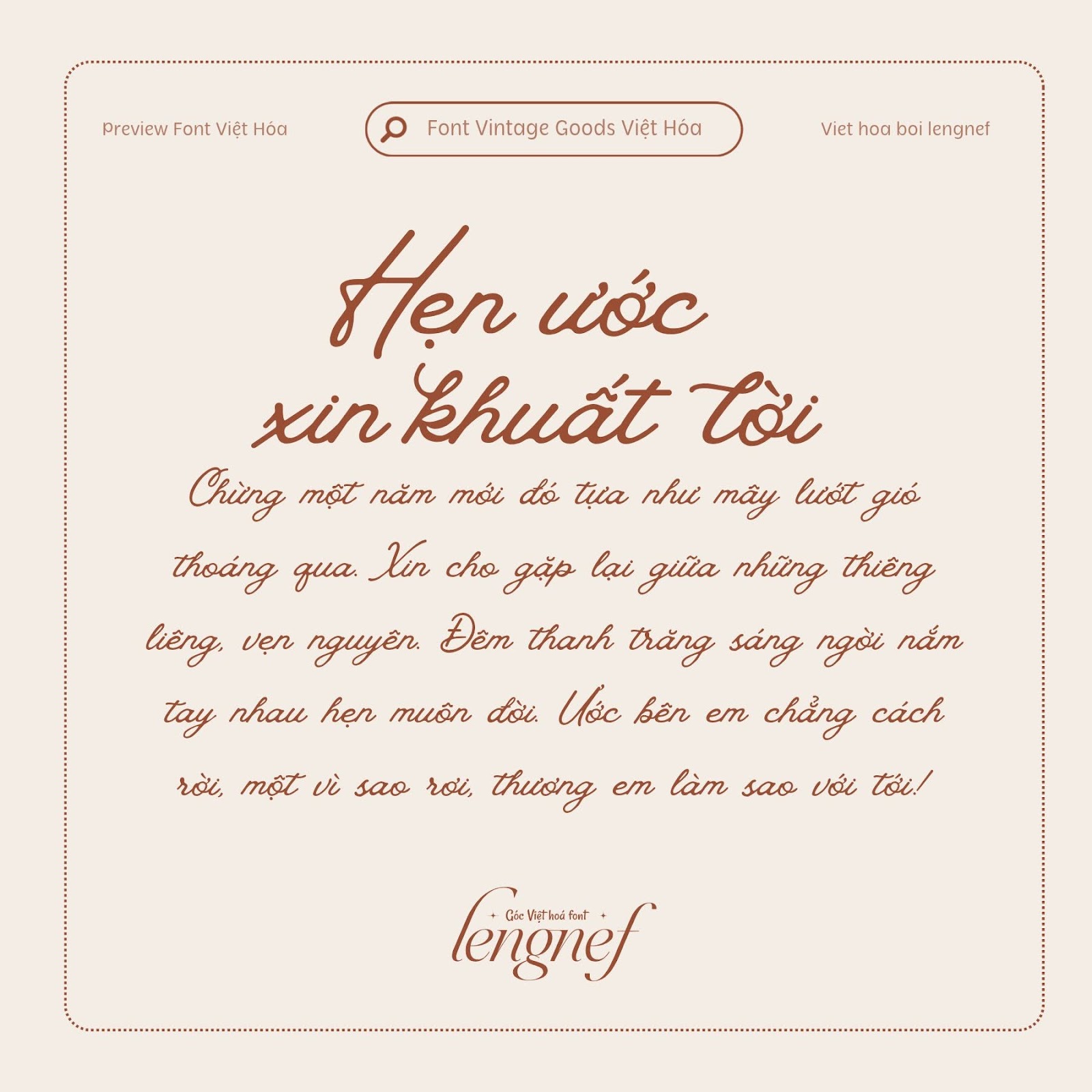
Share Font 30 || LF Vintage Goods
Vintage Goods được lấy cảm hứng từ những năm 1980, một thời kỳ tái khám phá và xem xét lại nghệ thuật thư pháp như một loại hình chữ viết, cũng như nhiếp ảnh và cảm xúc con người. Mục tiêu là mang đến những thiết kế đơn giản nhưng hiệu quả từ thời kỳ này. Những font chữ này rất phù hợp cho logo sản phẩm, logo thiệp cưới, logo thương hiệu quần áo, thiết kế vintage.